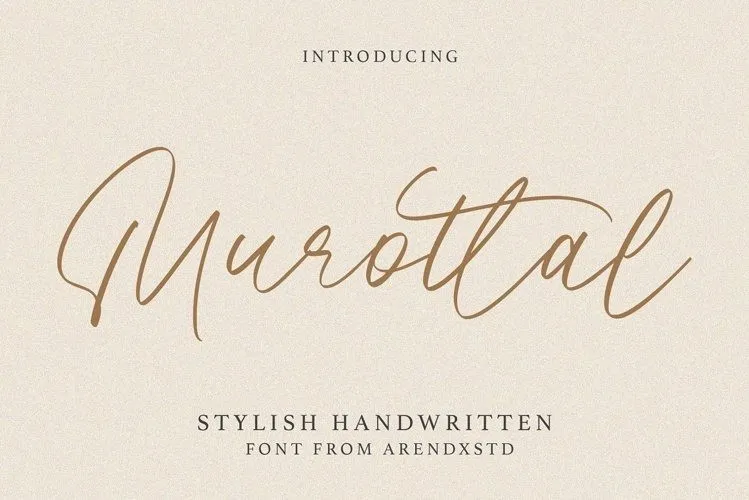
A Murottal é uma fonte script que traz a beleza do desenho à mão, com linhas afiadas e perfeitas. Desenvolvida por Arendxstudio, esta fonte moderna, elegante e tendenciosa enriquece qualquer projeto onde sejam utilizados – desde logotipos e camisetas até capas de livros e embalagens. O que torna a Murottal realmente especial é seu conjunto de caracteres OpenType com alternativas estilizadas, conjuntos estilizados e ligaturas, que permitem um nível de personalização e versatilidade incomparável. Seja para criar uma identidade visual impactante ou desenvolver design gráfico sofisticado, a Murottal é um recurso indispensável para qualquer designer em 99designs.